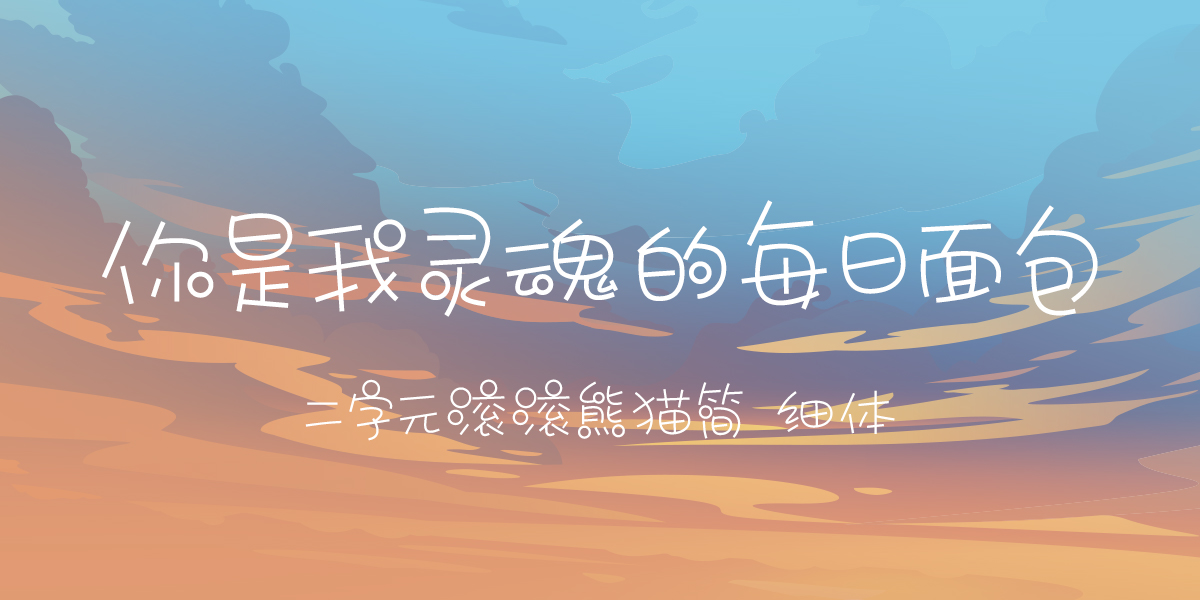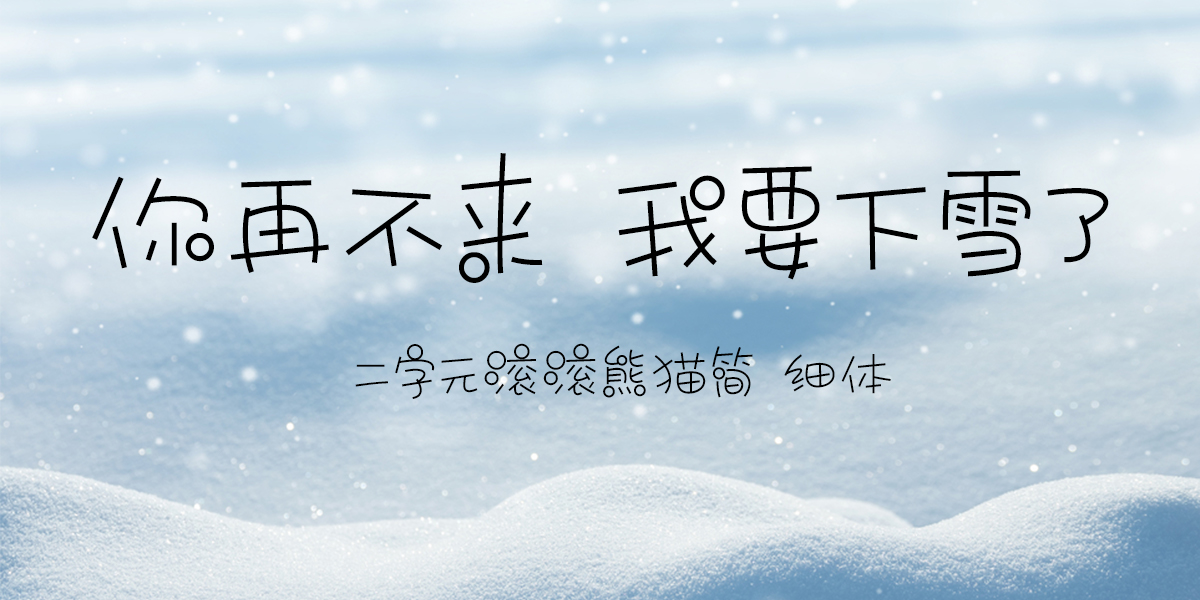
二字元滚滚熊猫简 细体
二字元滚滚熊猫简 细体,二字元滚滚熊猫简字形上,懒散而圆润,随意中带着亲近感;笔画上,简短直接,略带倾斜的横竖笔画,突显稚拙,辅以圆形元素烘托趣味,有着天然的稚嫩、萌呆。滚滚的“圆”,视觉上饱满而舒适;滚滚的“点”变成圈,字体面积对比增大,应用更醒目;滚滚的“横”和“竖”有俏皮的倾斜,使用场景更有亲和力。可广泛应用于休闲生活、食品、宠物用品、儿童用品等相关领域产品的设计与包装,也非常适用于卡通动漫、游戏、电商店铺等场景的设计应用。